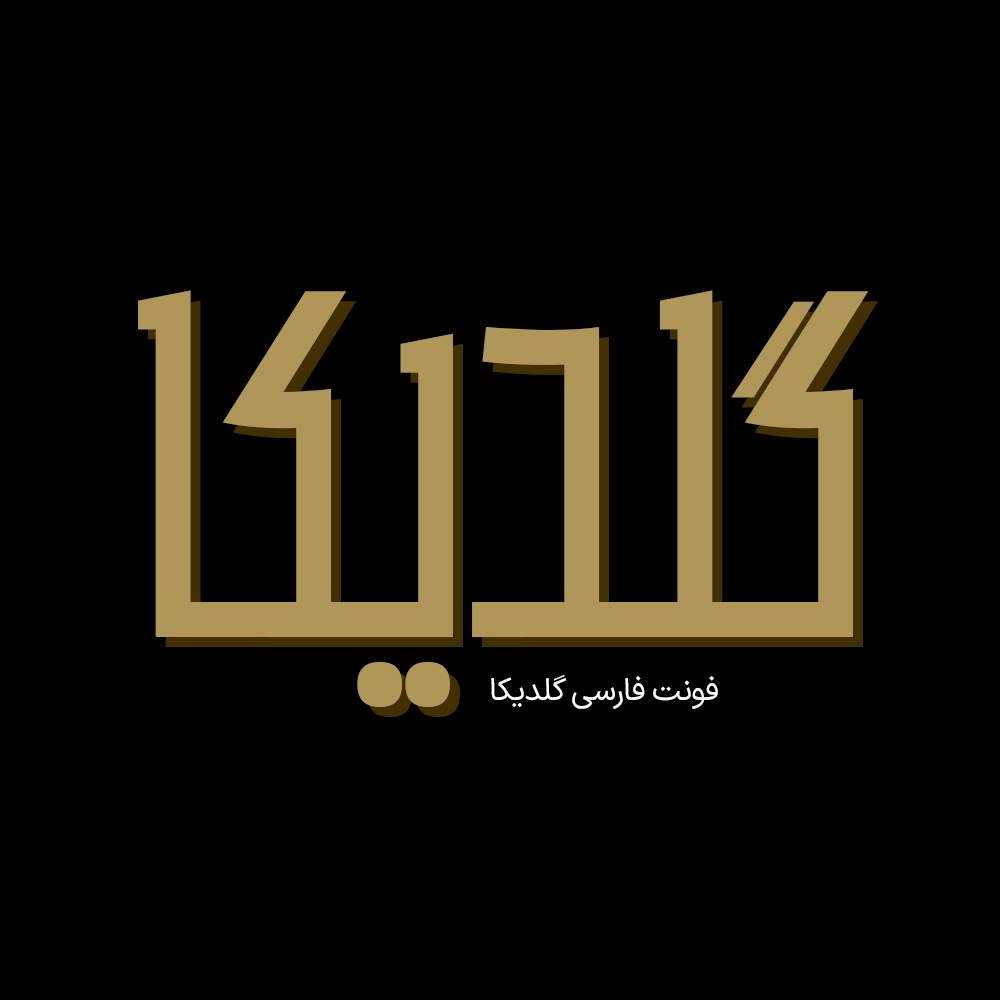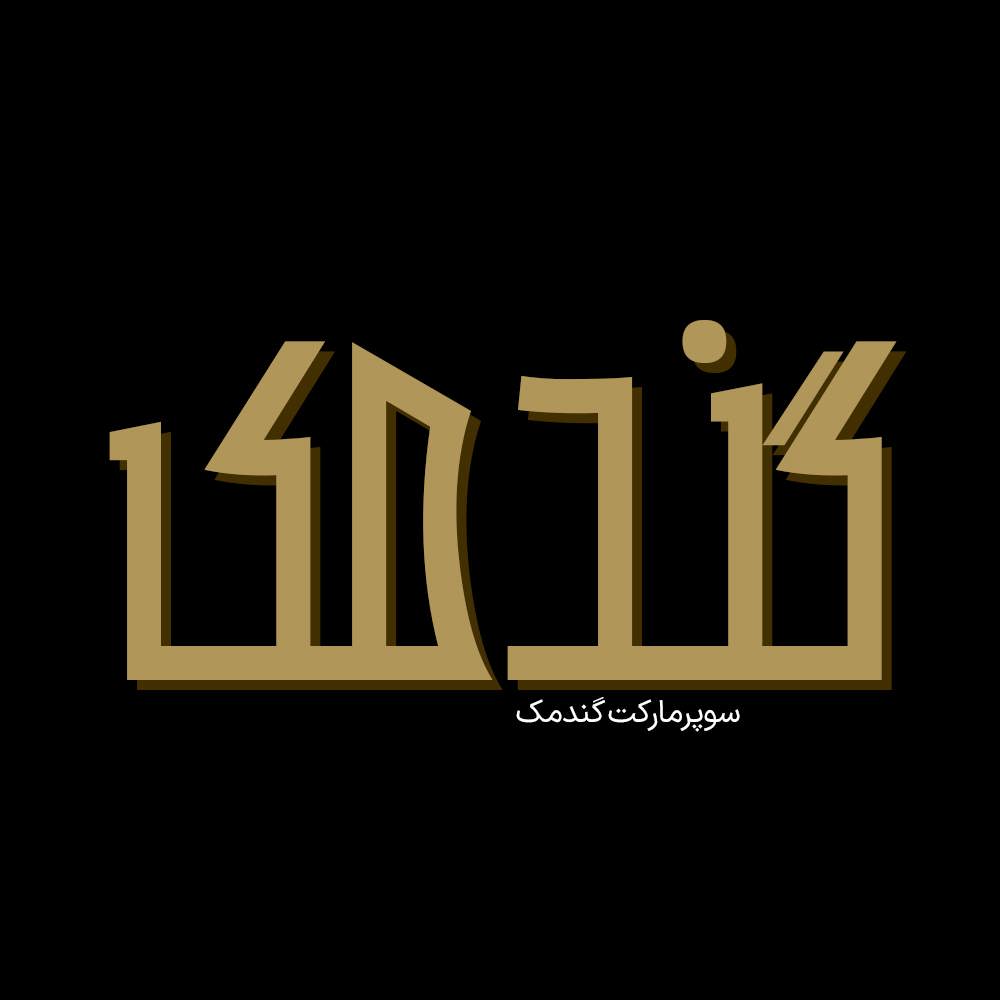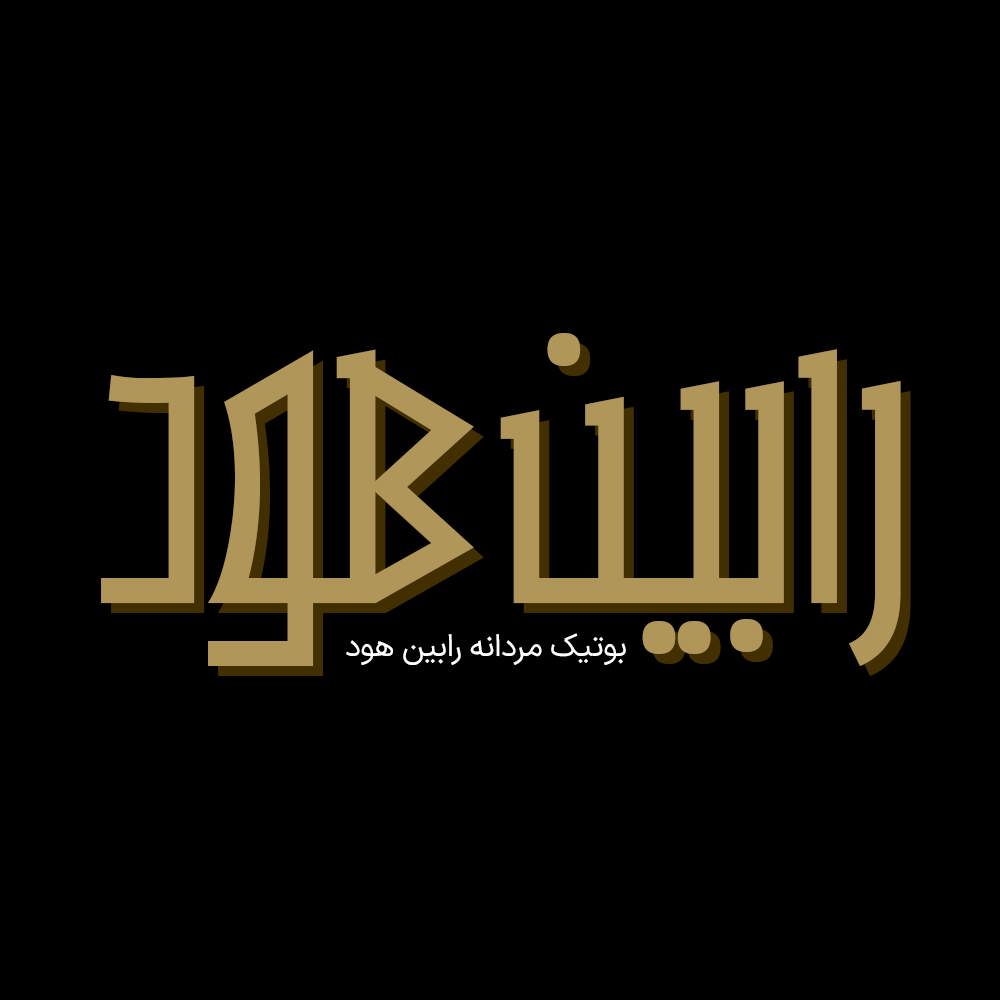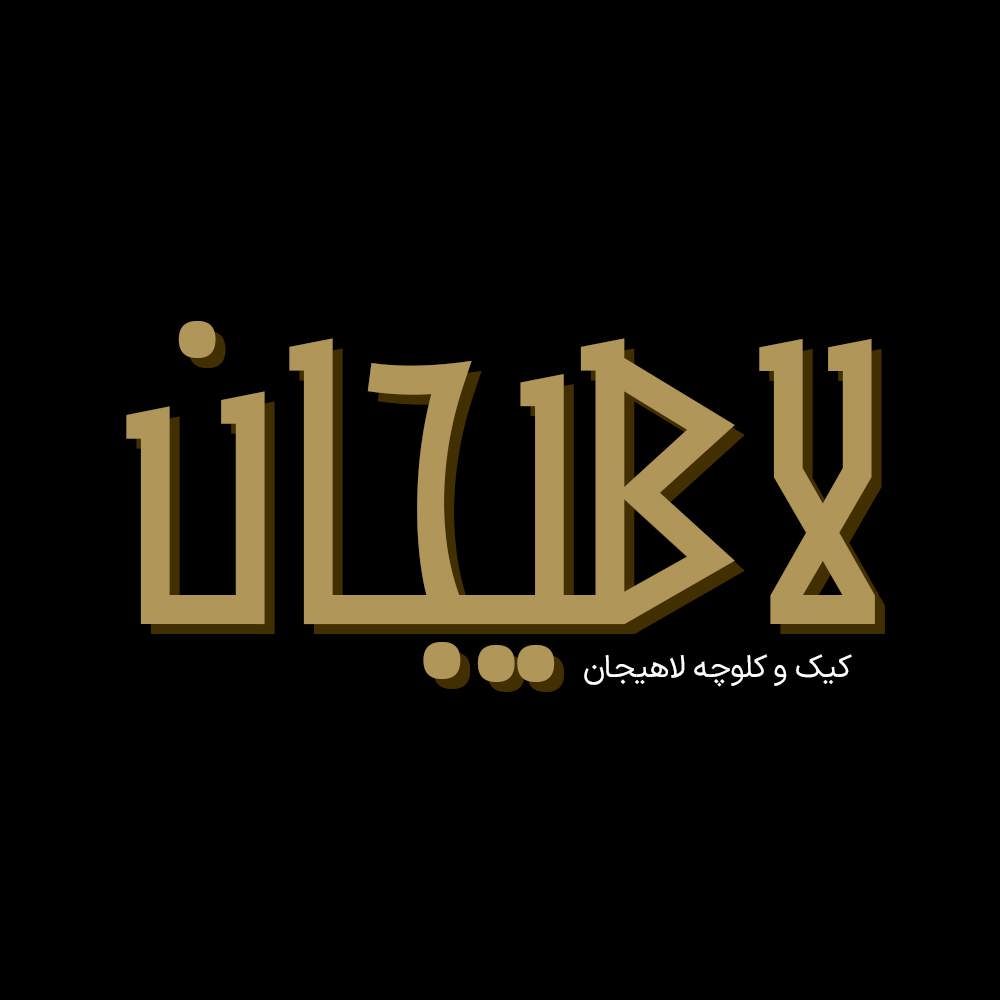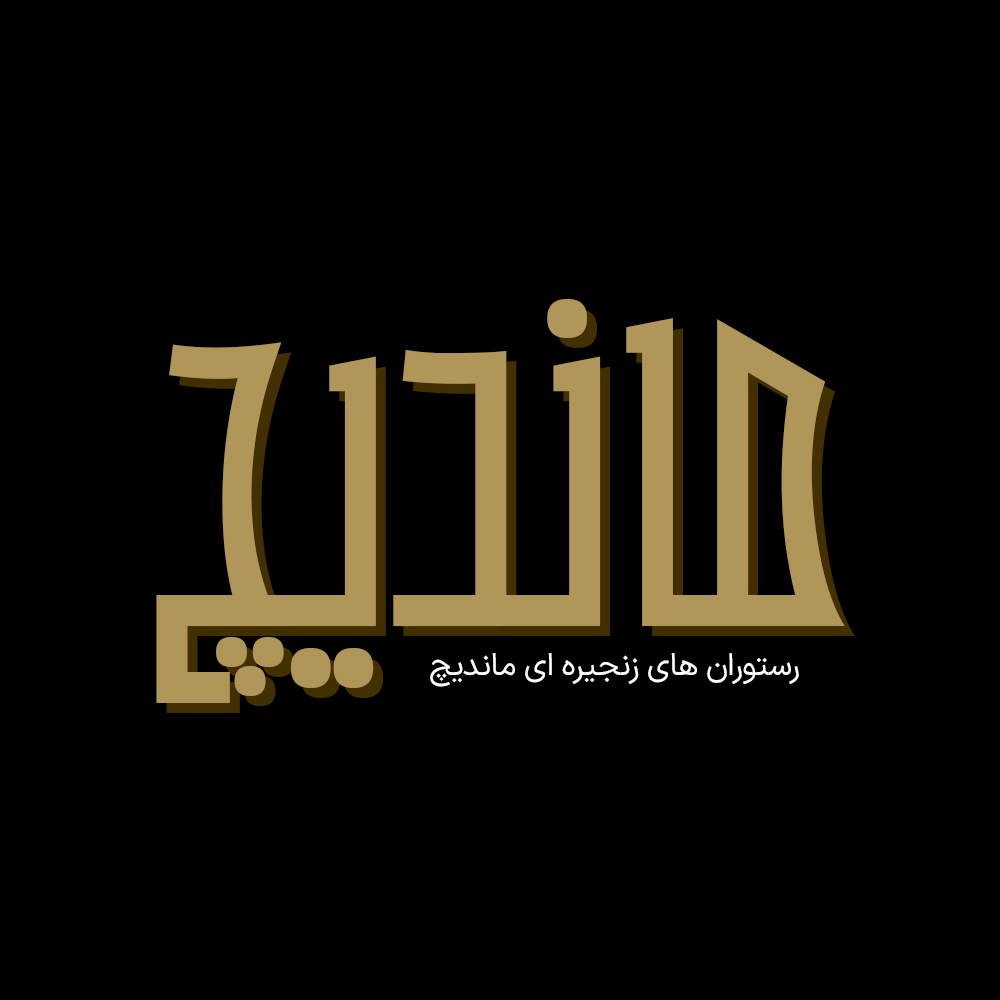
فونت فارسی گُلدیکا Goldika Font
فونت فارسی گُلدیکا شخصیتی جذاب و مستحکم دارد. در طراحی فونت گلدیکا از خط میخی الهام گرفته شده است که مخصوص طراحی لوگوتایپ و طراحی های…
فونت فارسی گُلدیکا شخصیتی جذاب و مستحکم دارد. در طراحی فونت گلدیکا از خط میخی الهام گرفته شده است که مخصوص طراحی لوگوتایپ و طراحی های مختلف همچون کتاب و تولید محتوای متن های کوتاه و عناوین می باشد. این فونت با فرمهای سخت و نرم خود مناسب استفاده در لوگوهای نوشتاری می باشد. همچنین از این فونت در طراحی تابلوهای چلنیوم هم به دلیل ساختار منحصر به فردش می توانید استفاده کنید. در ادامه برای شما نمونه تایپ های این محصول حرفه ای رو آماده کردیم که میتونید مشاهده کنید.
پیشنمایش و نمونه تایپ های فونت گلدیکا